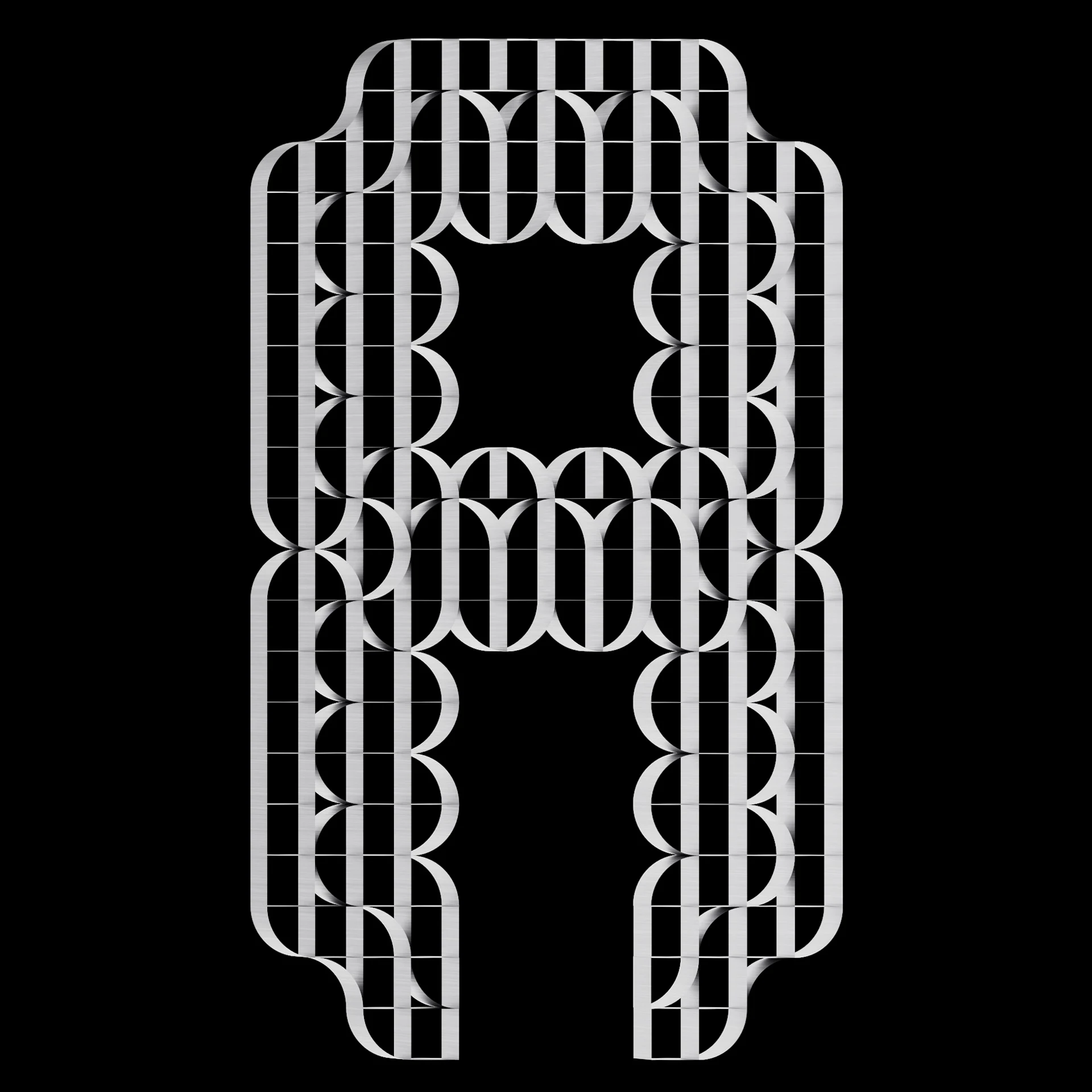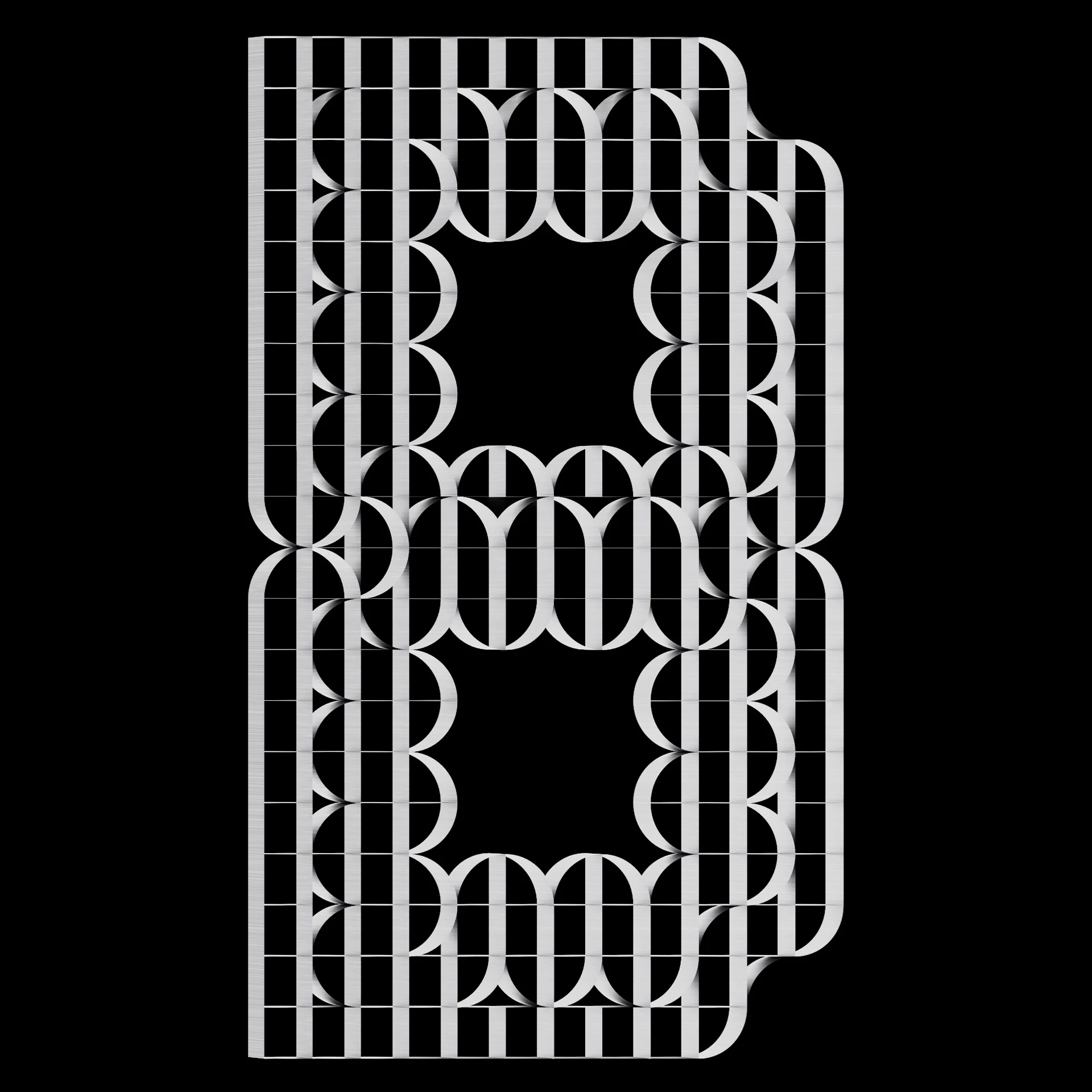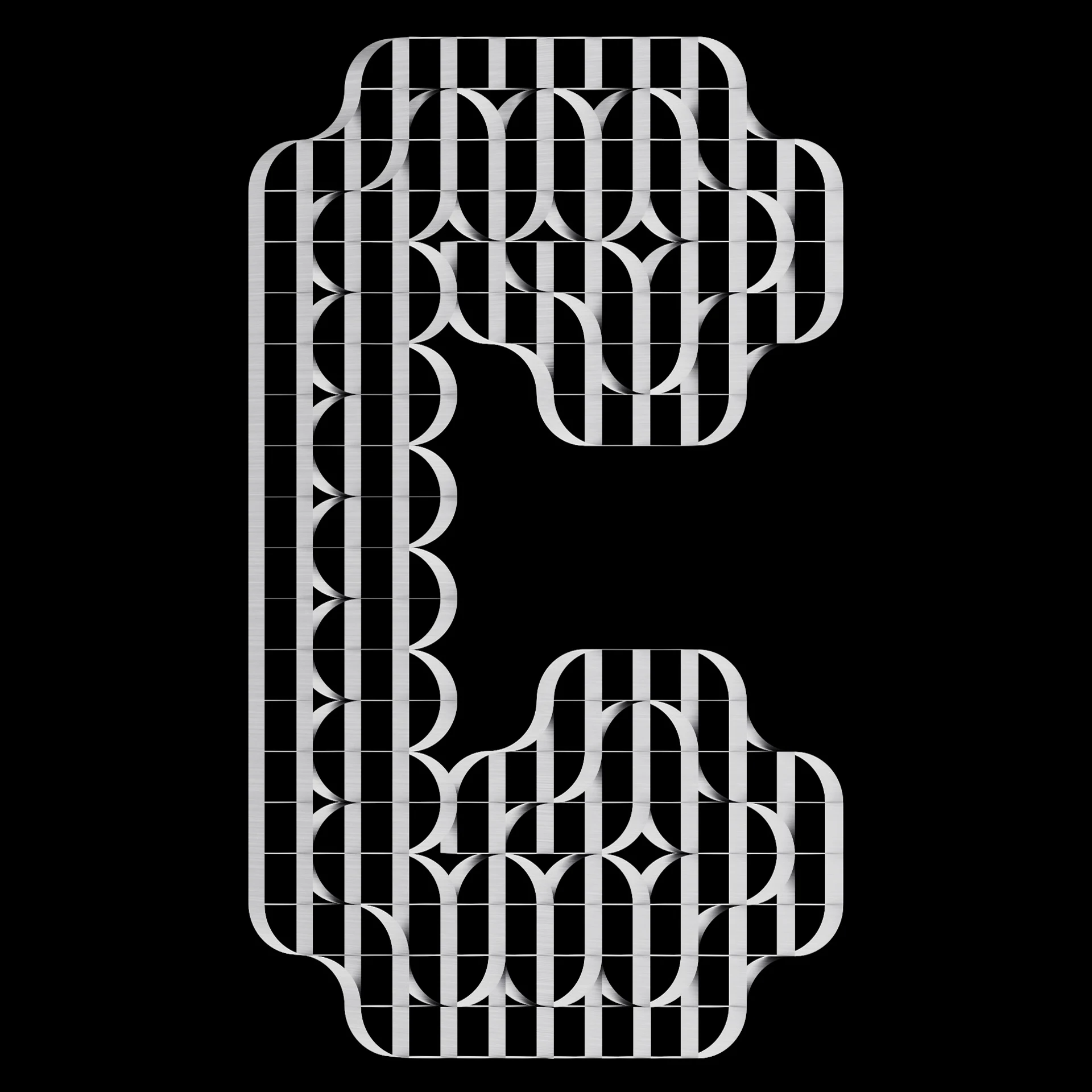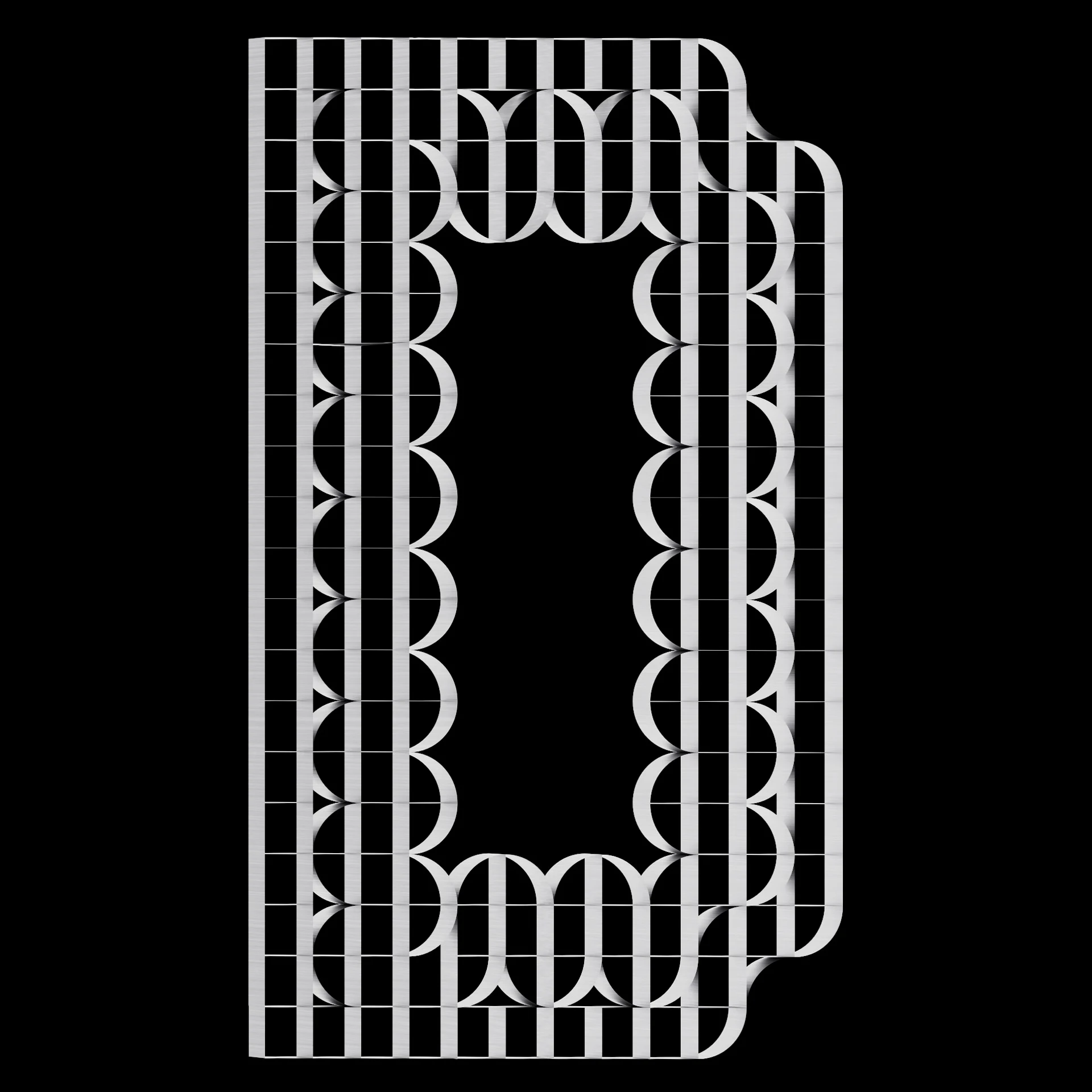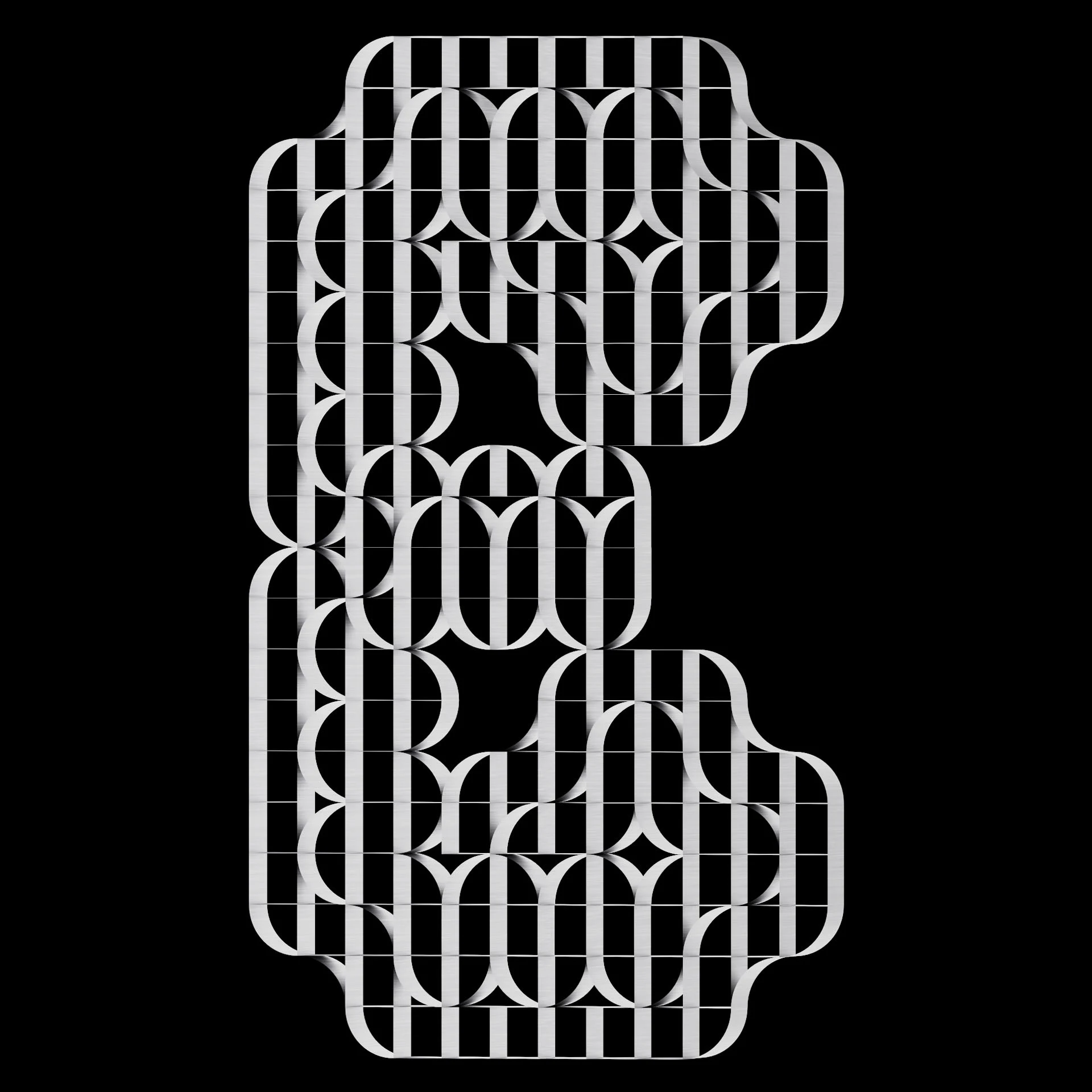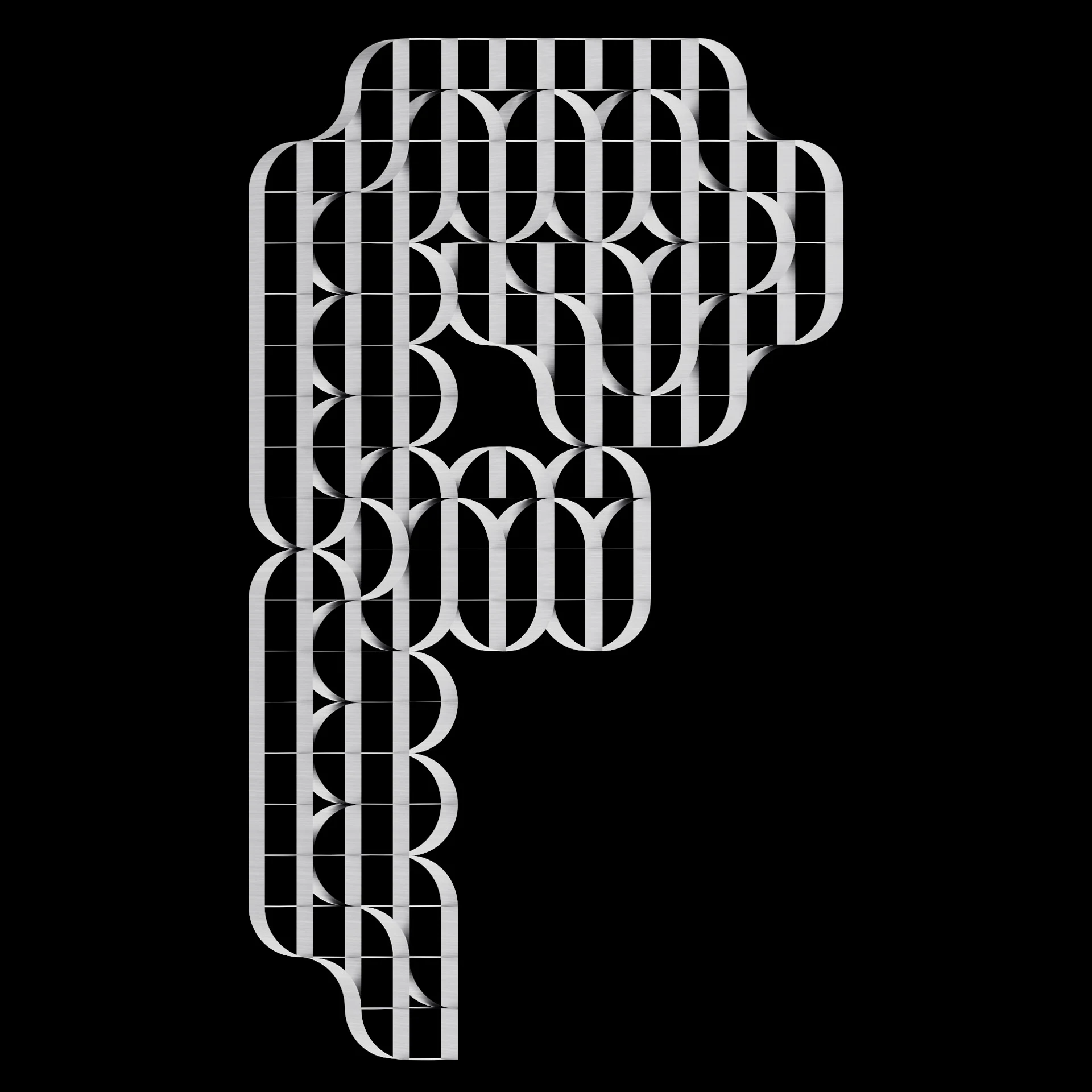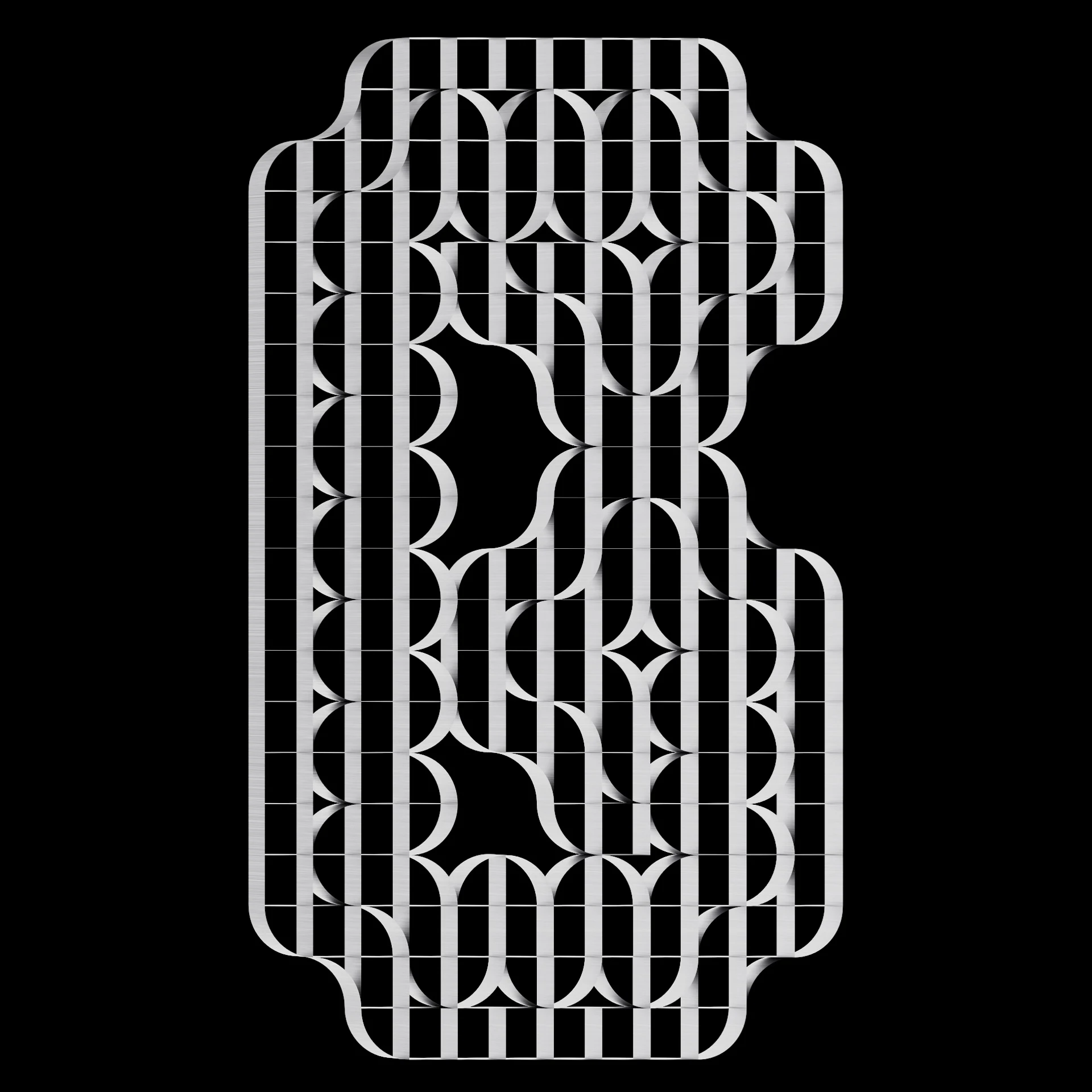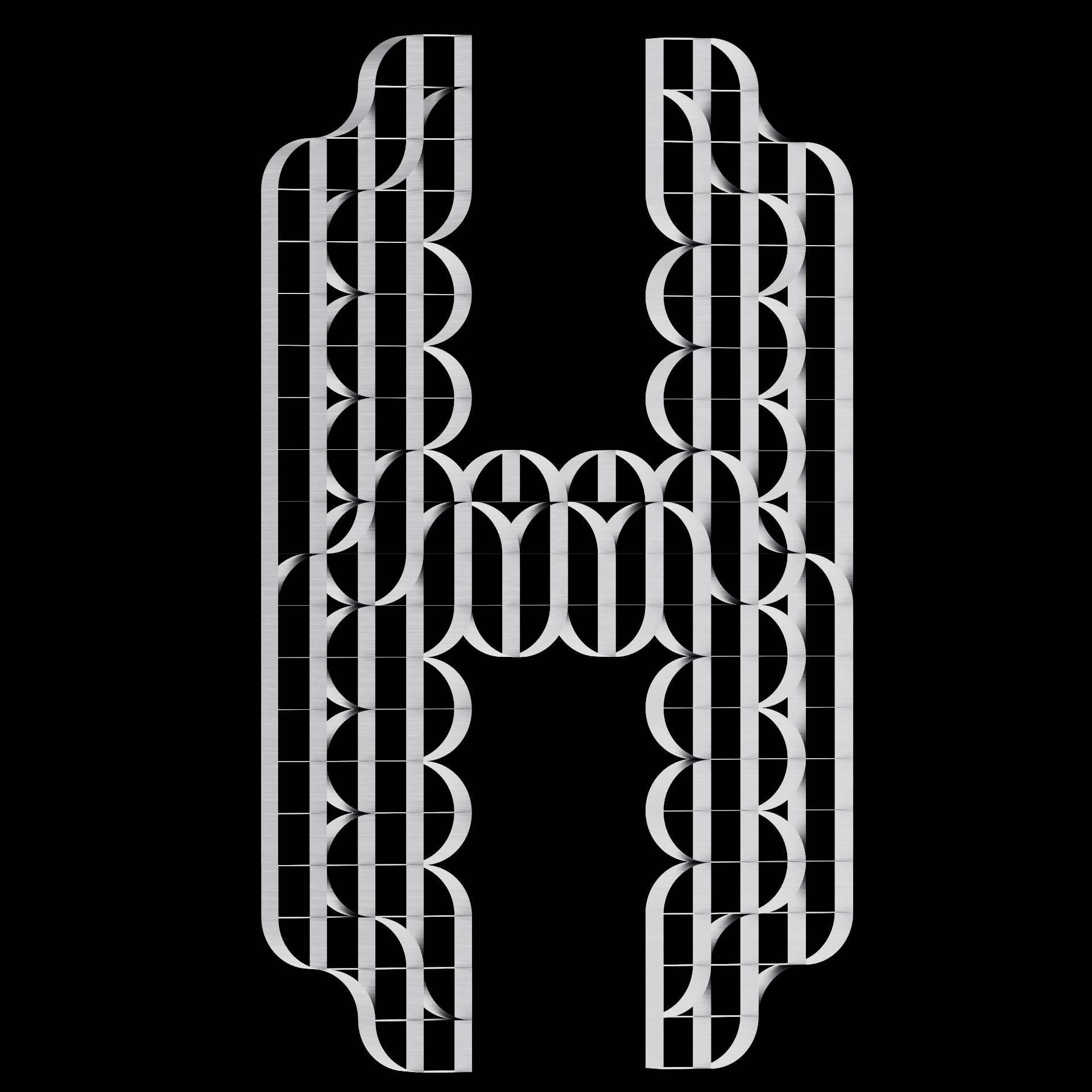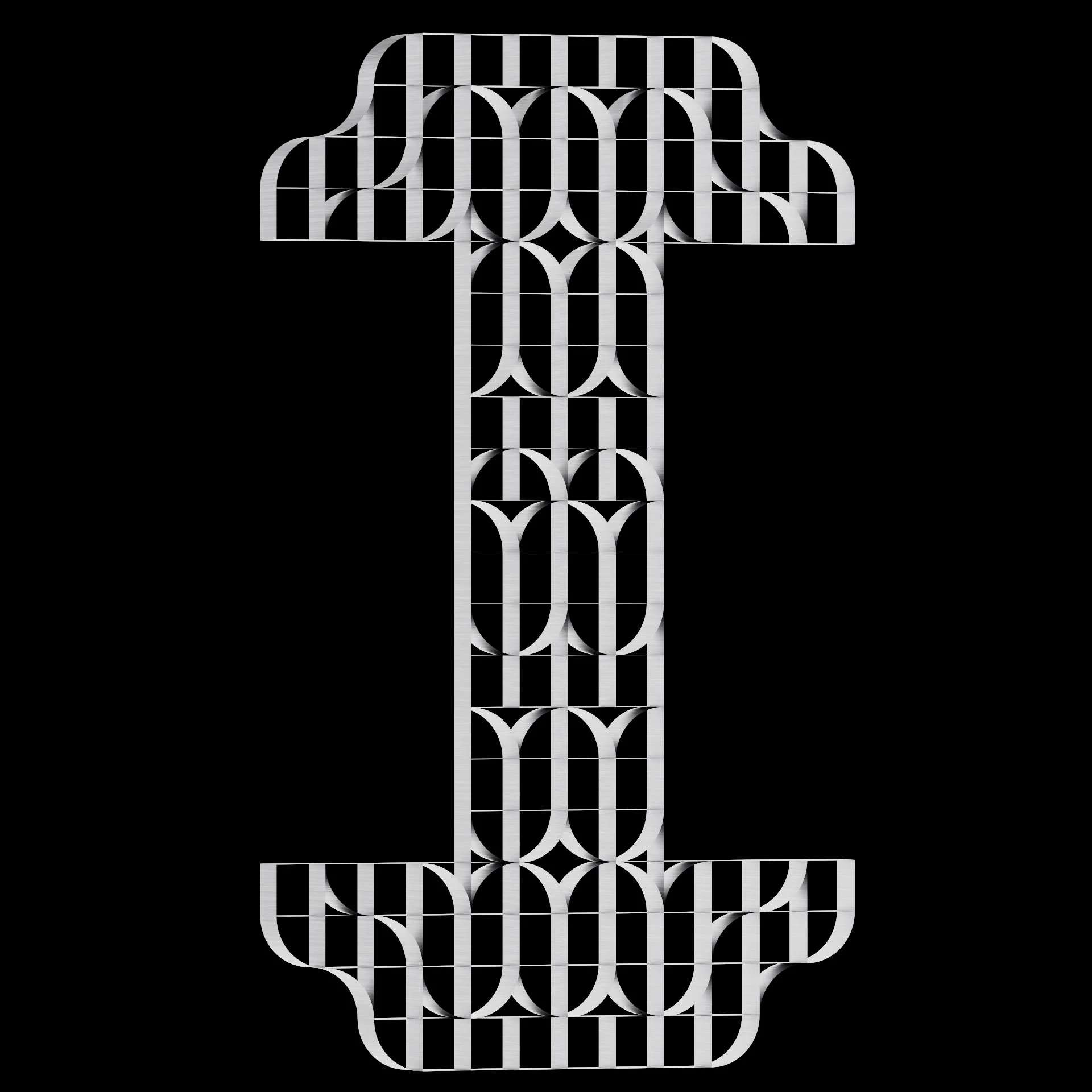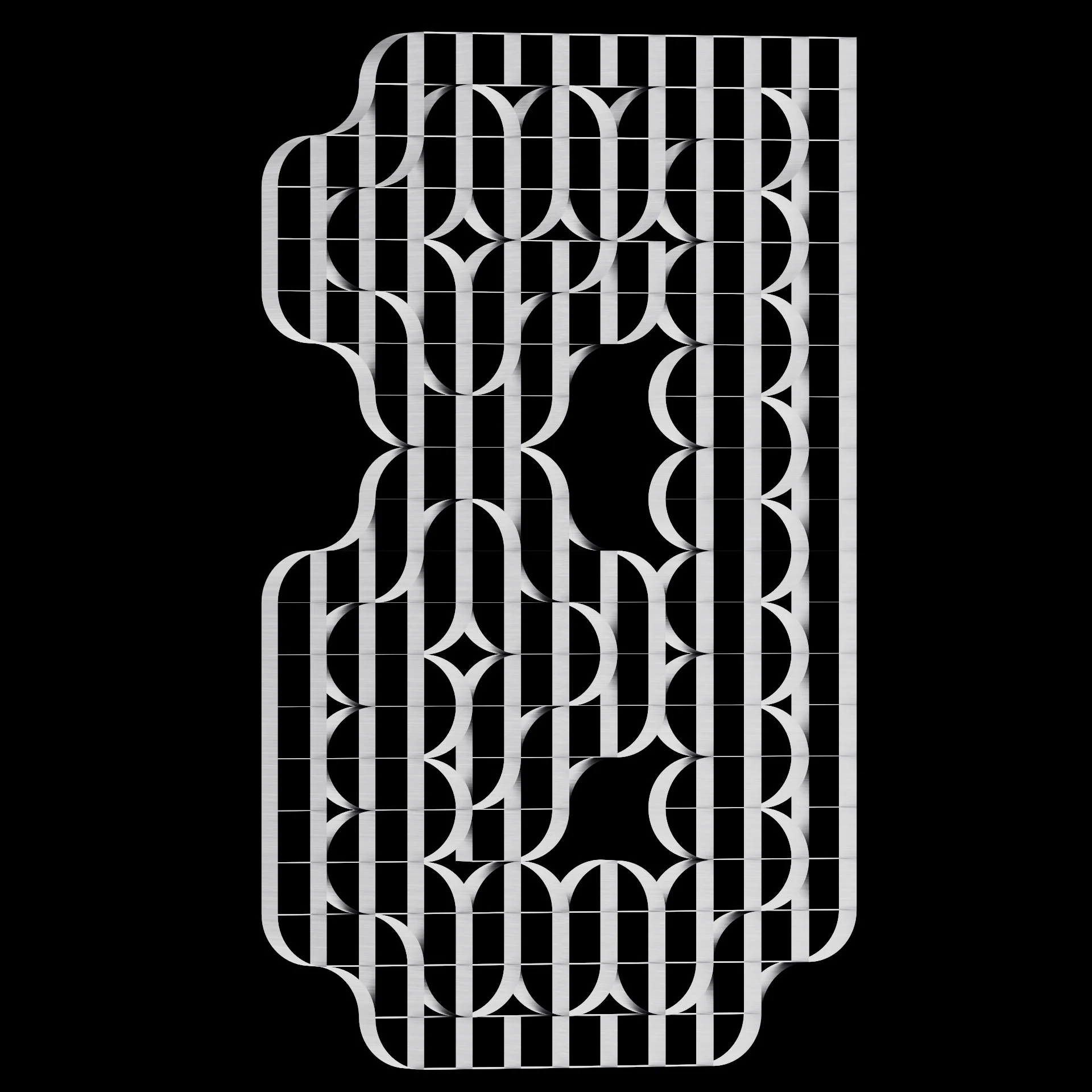
Aplicación del sistema FORM publicado por Martin Lorenz en Flexible Visual Systems (Lars Müller Publishers, 2019). Un único módulo — líneas verticales cruzadas por arcos elípticos alternos — se repite en trama continua; la silueta de cada carácter lo recorta. La pregunta que plantea es si una sola unidad puede sostener un alfabeto completo.
La tipografía modular como práctica sistemática tiene antecedentes directos en la Bauhaus — los tipos de plantilla de Albers, el universal de Bayer — y en las exploraciones del estilo internacional. El sistema FORM de Lorenz opera en esa misma lógica: un elemento repetido que genera variedad formal a través de la máscara. Este ejercicio aplica el sistema con el alfabeto latino completo y los dígitos 0–9, comprobando dónde el módulo único es suficiente y dónde exige compromisos formales.
El módulo consiste en una columna de líneas verticales paralelas cruzadas perpendicularmente por arcos elípticos en posición alterna. El campo se genera por repetición regular. La silueta de cada carácter actúa como máscara: el interior de la letra es siempre el mismo campo modular; el exterior es negro sólido.
Lectura del sistema FORM → selección y construcción del módulo base → generación del campo de repetición → aplicación de la silueta por carácter → ajuste de terminaciones en esquinas → composición del specimen completo.